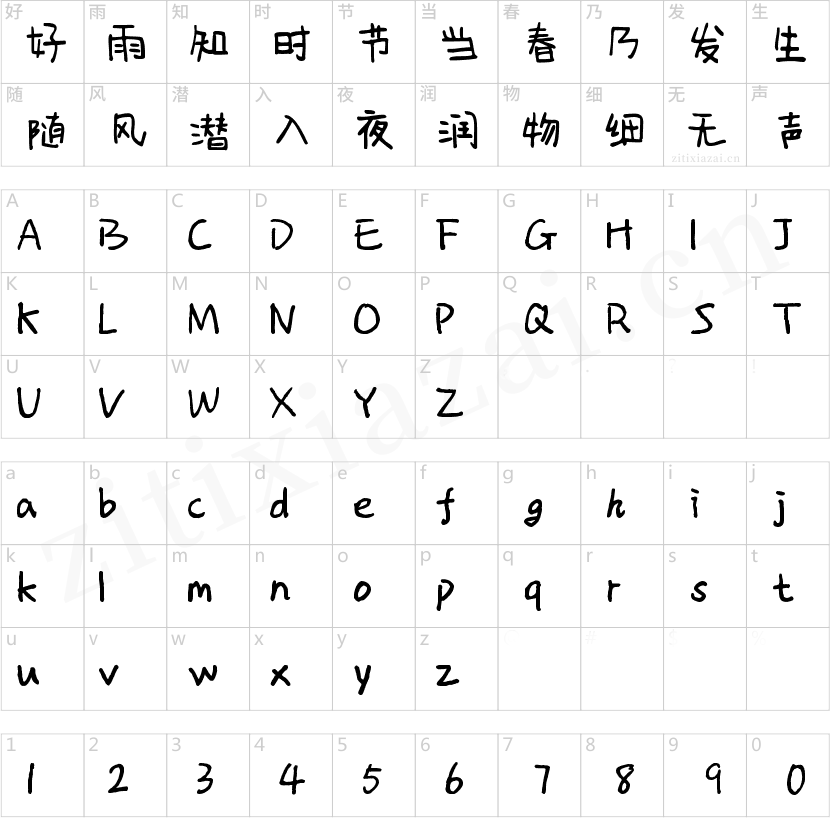
Aa乔乔体
Aa乔乔体字体
Aa乔乔体是一款非常具有艺术性的字体,它的设计灵感来源于对古典艺术的研究,同时又融入了现代字体设计的元素。字形优美,笔画粗细变化自然,给人以大气、典雅的感觉。Aa乔乔体是一款既传统又现代的字体,它的设计充满艺术感,美观大方,实用性也非常强。无论是对于设计师还是对于普通读者来说,都是一种非常不错的字体选择。Aa乔乔体适合用于具有艺术感的场合,比如海报、宣传单张、书籍封面等。由于其字形流畅且具有动态感,也适合用于大量的文本排版,如报纸、杂志等。